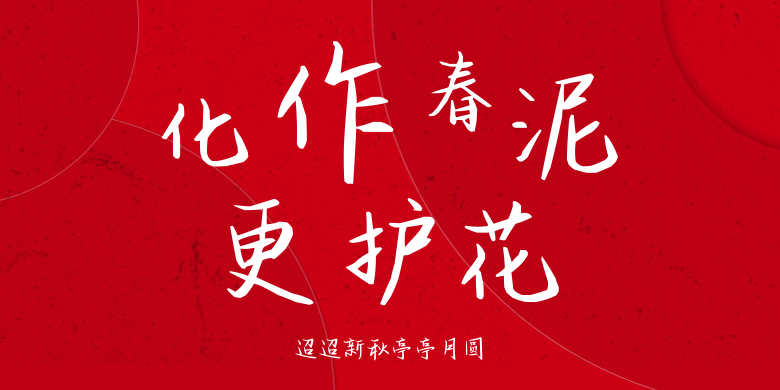
迢迢新秋亭亭月圆
迢迢新秋亭亭月圆,这款字体结构工整、笔画清晰,兼顾美观与易读性,适用于标题、正文、海报、包装、LOGO 等多种场景。字形优雅稳定,风格百搭耐看,适配日常排版与创意设计,让文字呈现更舒适、更具质感。迢迢新秋亭亭月圆一笔一画,皆是细节,以均衡的比例、流畅的线条打造舒适视觉体验,字形端正大气,风格简约现代。无论是商业设计、品牌宣传还是日常排版,都能轻松驾驭,让文字更有格调与力量。迢迢新秋亭亭月圆字体下载。